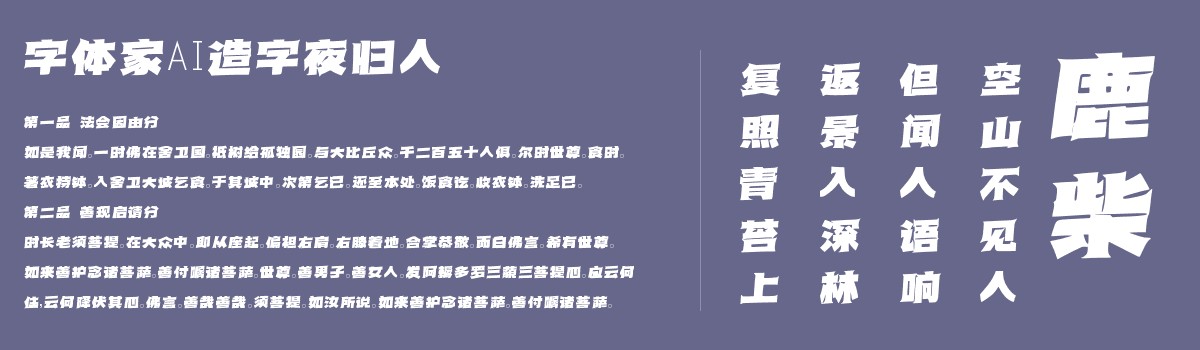
字体家AI造字夜归人
字体家AI造字夜归人是一款由字体家AI神笔造字生成的艺术字体,此字体笔画粗细均匀,如刀切般方头方尾,无圆润弧度。转折处皆为利落直角,线条刚直挺括,似标尺量出般规整。结构端正,重心沉稳,无倾斜偏移。整体无丝毫花哨装饰,仅以均匀线条与平衡架构立足,简洁中透着庄重,刚劲里藏着可靠,如磐石般沉稳,似钢轨般明晰,给人稳定、清晰、有力的视觉感受。适合用于一些广告标题、平面文案、海报标题、网页广告用字的编辑。